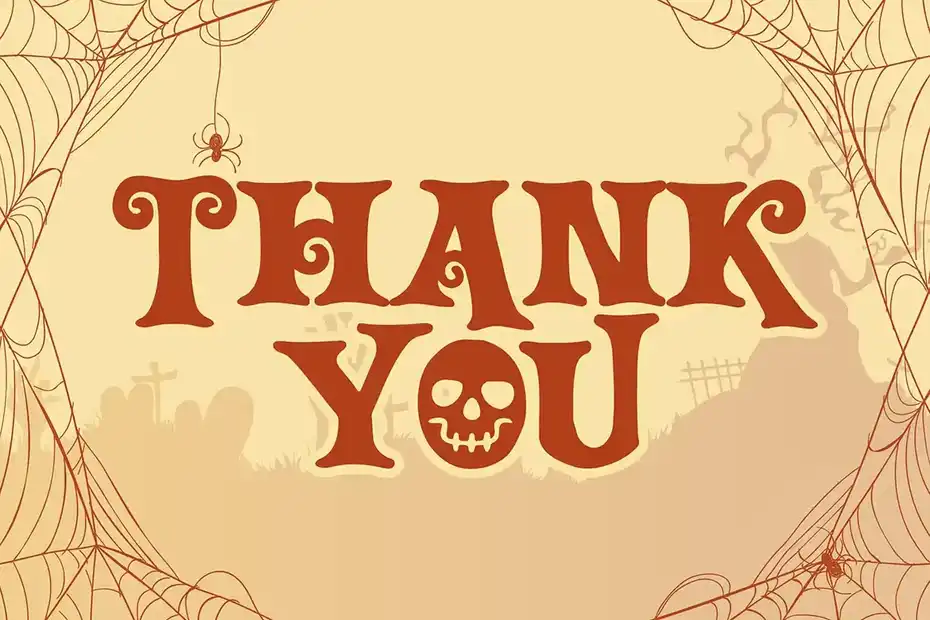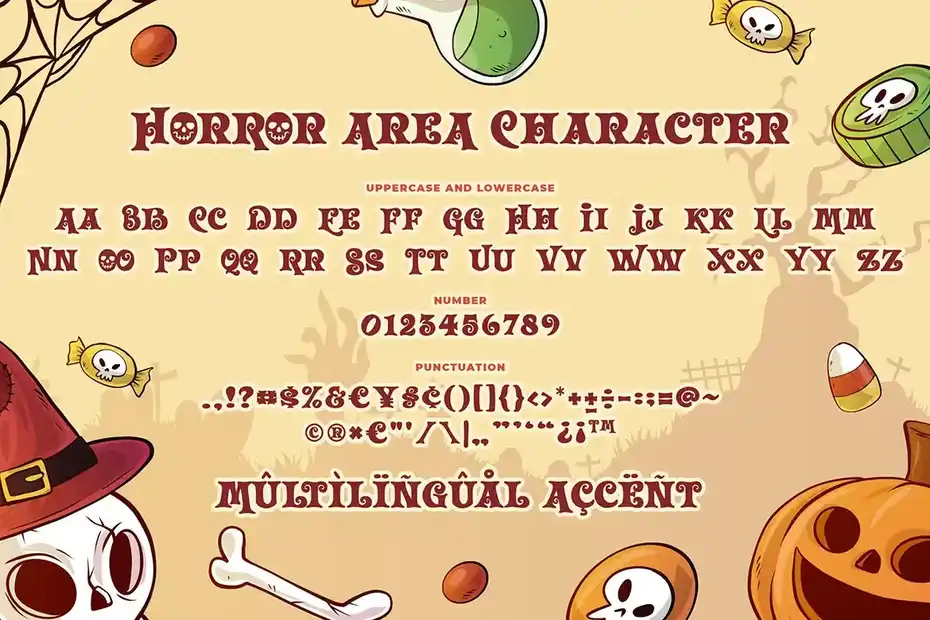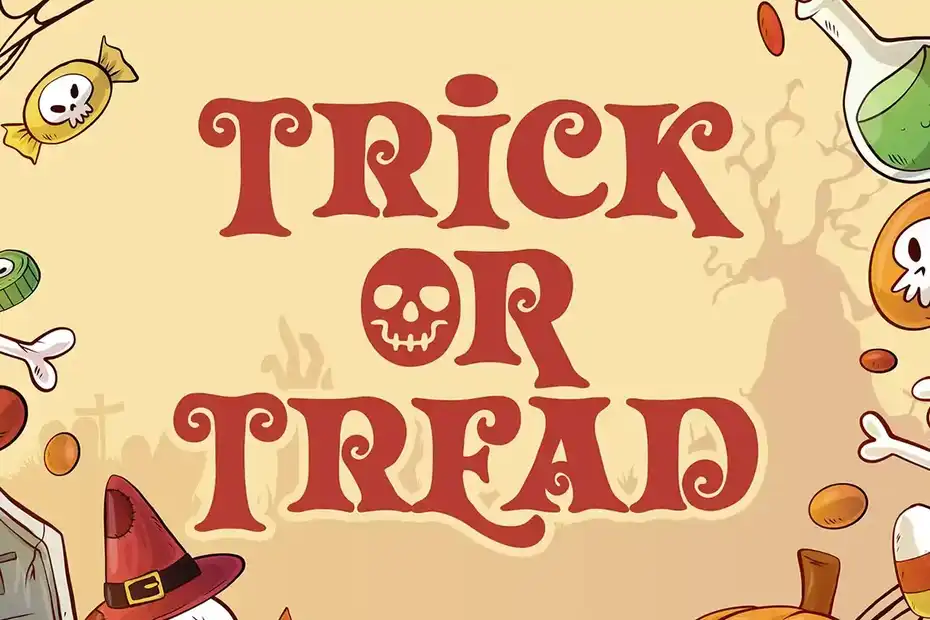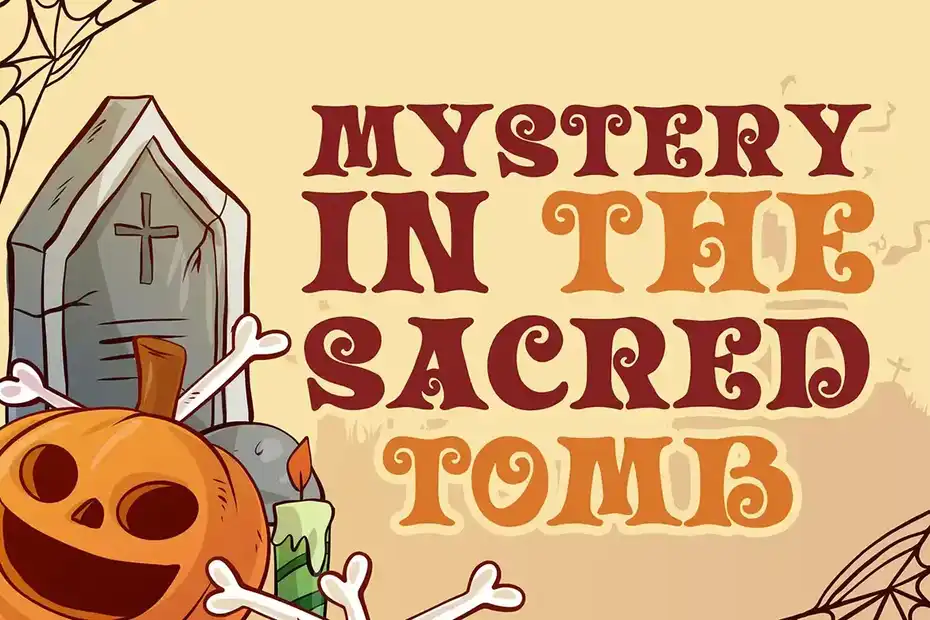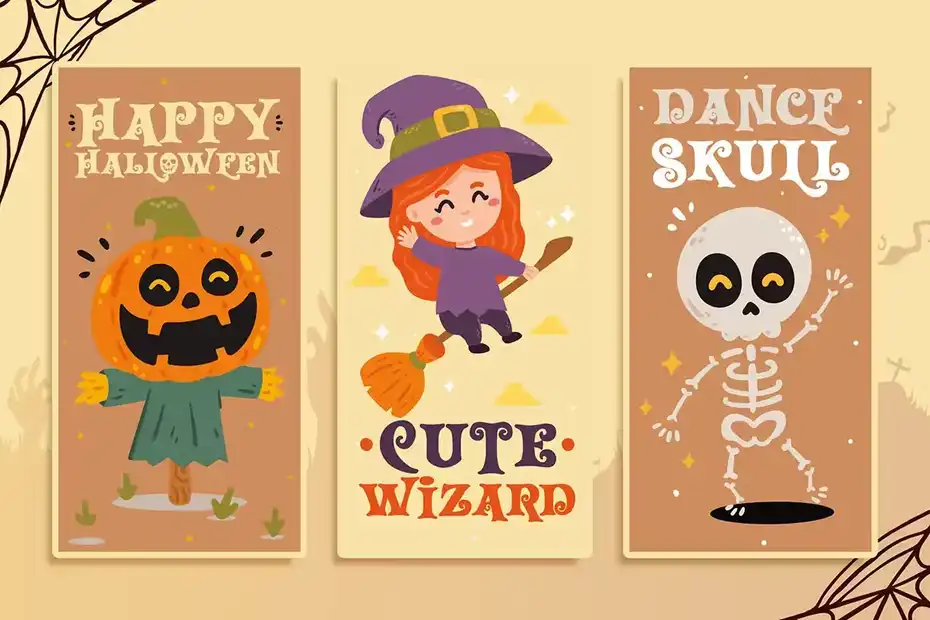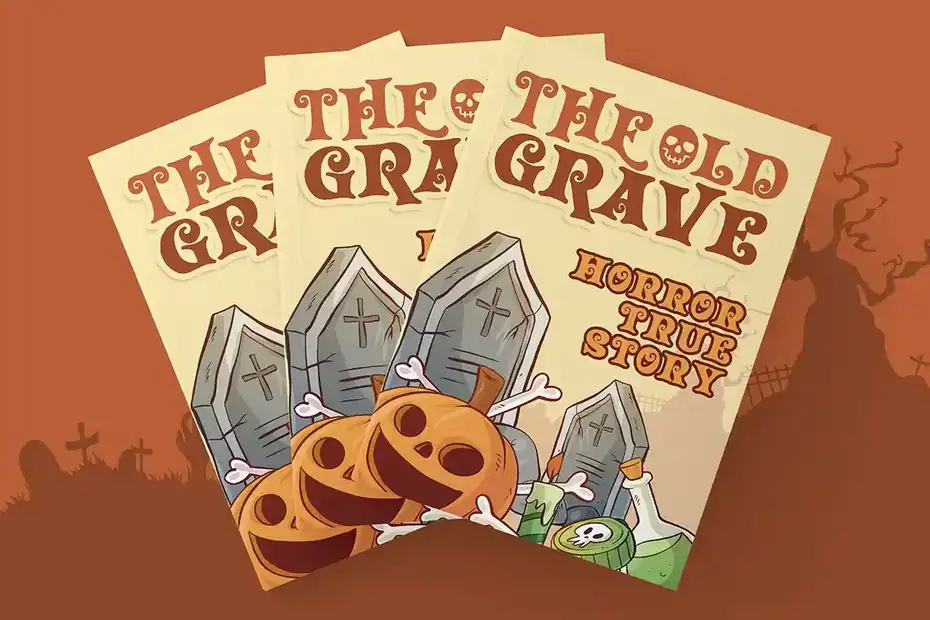
فونت انگلیسی ترسناک Horror Area a Plaful Horror Font : این مجموعه شامل یک فونت انگلیسی ترسناک است که برای تم هالوون، ترسناک، جلد کتاب، کتاب کودکان، کمیک، پوستر، بسته بندی، کالا، لوگو و غیره مناسب میباشد.
• سبک: Serif